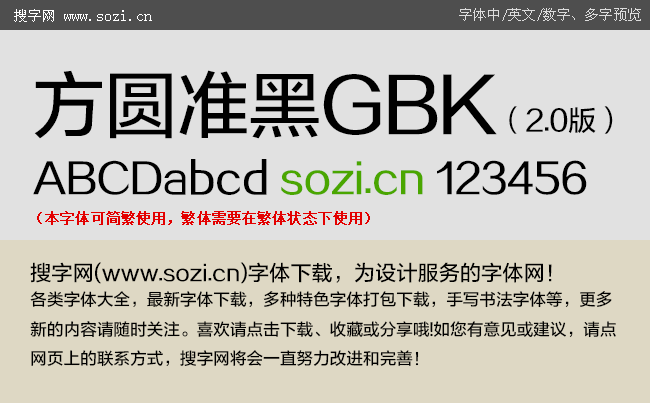
方圓準(zhǔn)黑GBK
搜字網(wǎng)提供一款方圓準(zhǔn)黑GBK下載,方圓準(zhǔn)黑是一款標(biāo)準(zhǔn)的中黑字體,該字體端正大方,識(shí)別性強(qiáng),整體風(fēng)格出色,且GBK標(biāo)準(zhǔn)收錄文字更全,適用于廣告設(shè)計(jì)、名片設(shè)計(jì)、包裝印刷、產(chǎn)品設(shè)計(jì)等應(yīng)用。